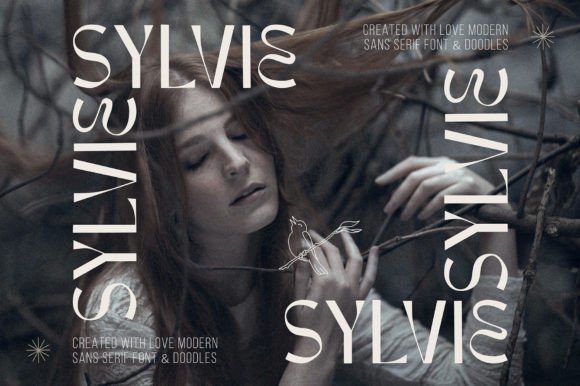
Sylvie
Việc tìm kiếm các thành phần thiết kế phù hợp có thể là một thách thức, nhưng Sylvie cung cấp một bộ sưu tập đặc biệt giúp nâng tầm công việc của bạn ngay lập tức.
Được chế tác với độ chính xác cao, Sylvie cung cấp các vector sạch, kiểu chữ mượt mà và giấy phép thương mại để bạn yên tâm.